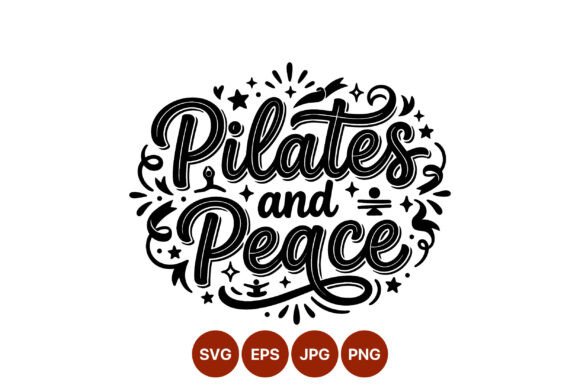
Pilates and Peace Calligraphic Lettering
Nếu bạn đang tìm kiếm các tài nguyên chất lượng cao như Pilates and Peace Calligraphic Lettering, gói cao cấp này là một lựa chọn tuyệt vời cho các dự án sáng tạo của bạn.
Được chế tác với độ chính xác cao, Pilates and Peace Calligraphic Lettering cung cấp các vector sạch, kiểu chữ mượt mà và giấy phép thương mại để bạn yên tâm.